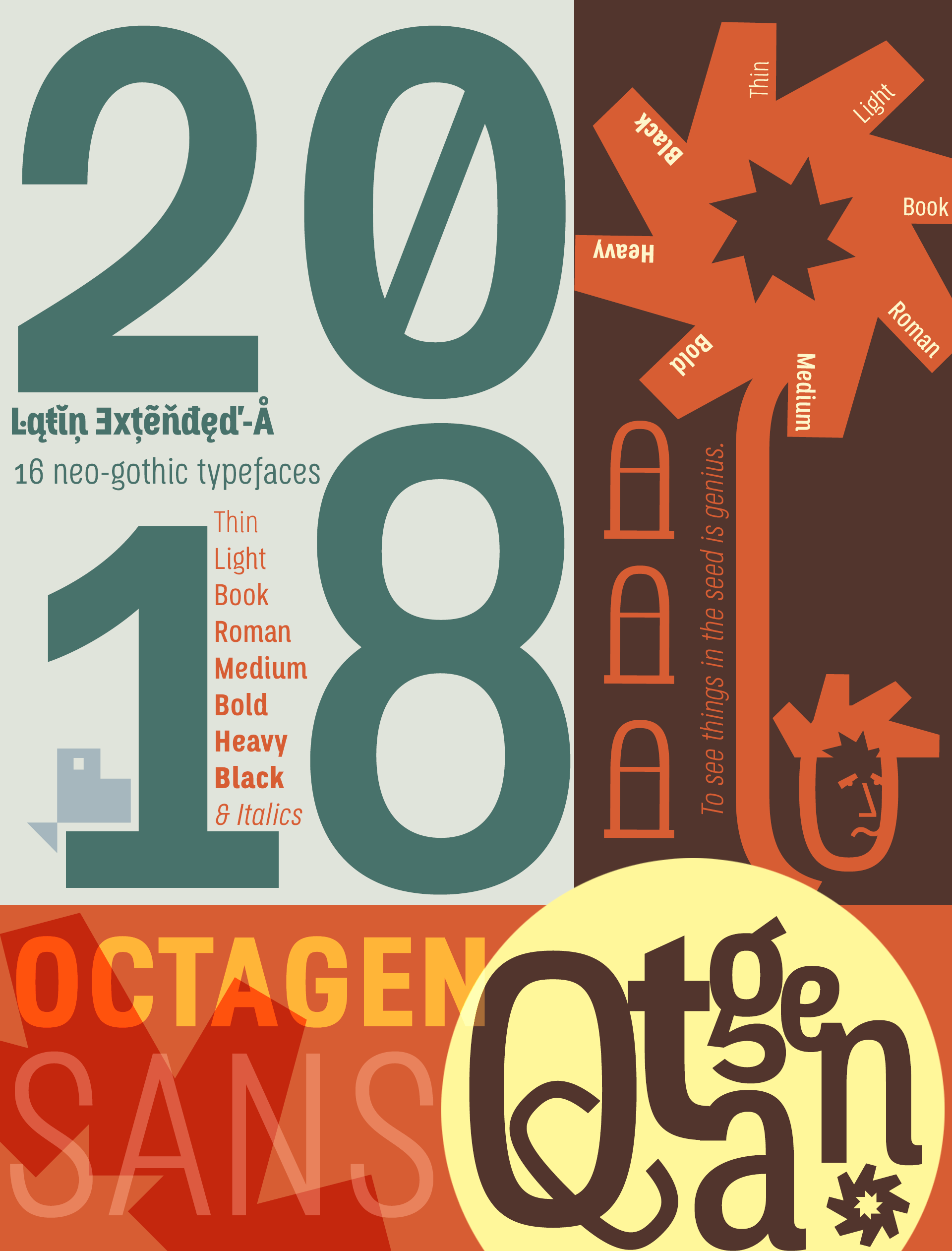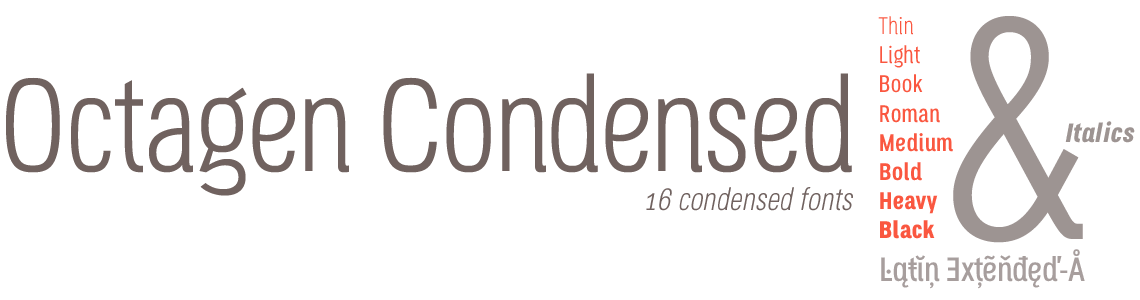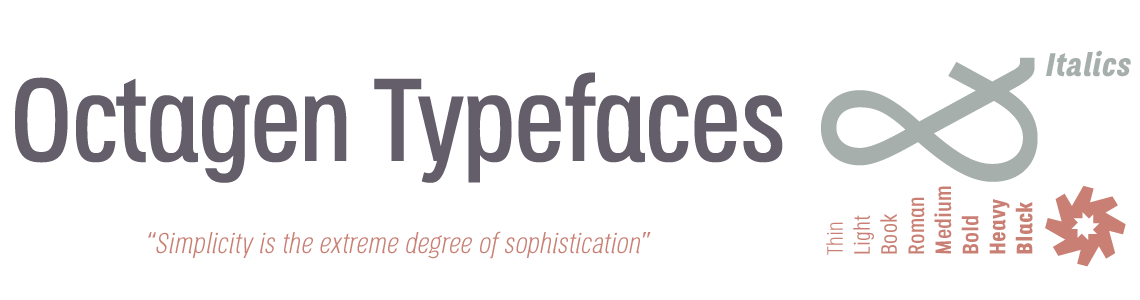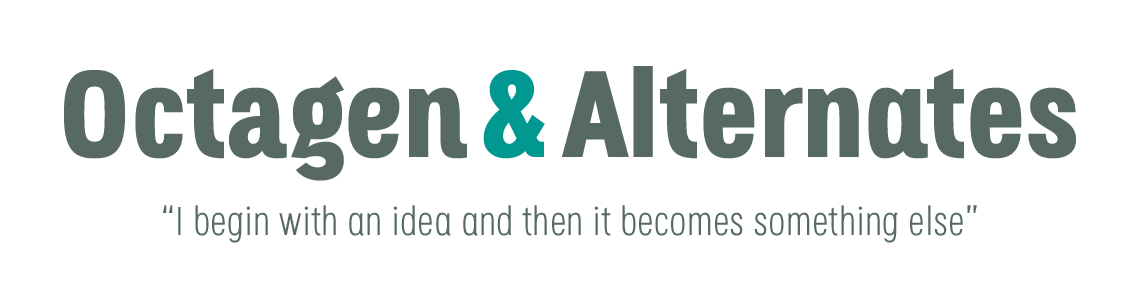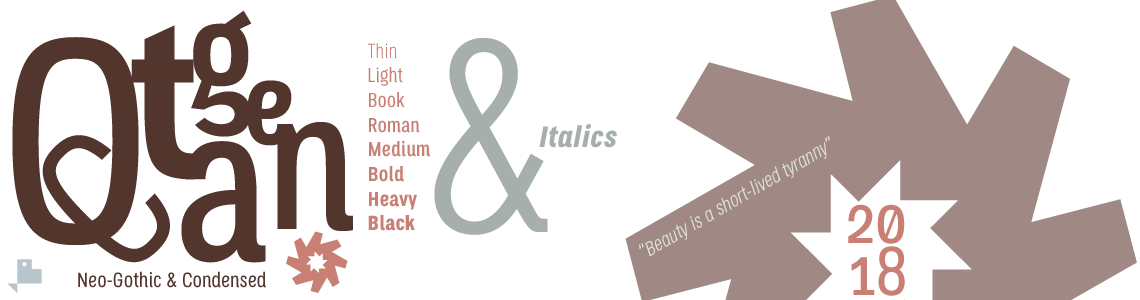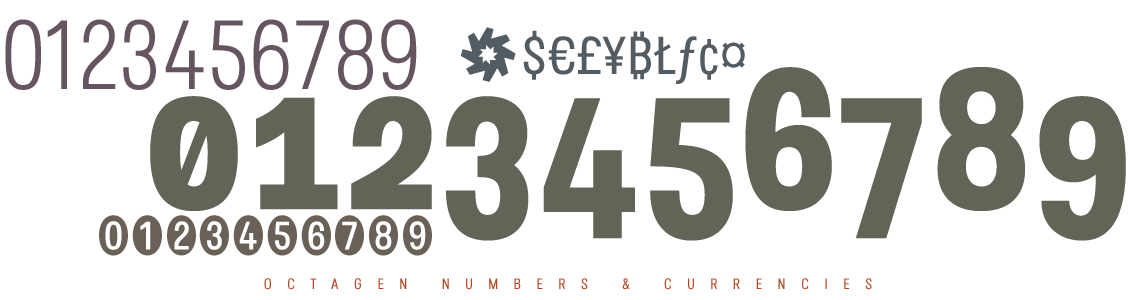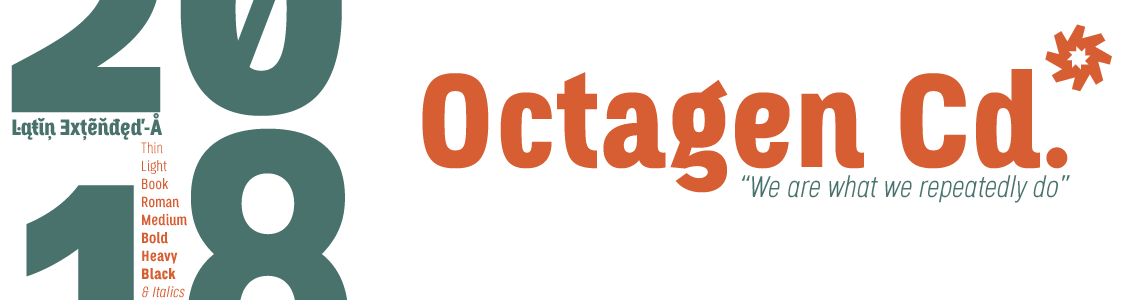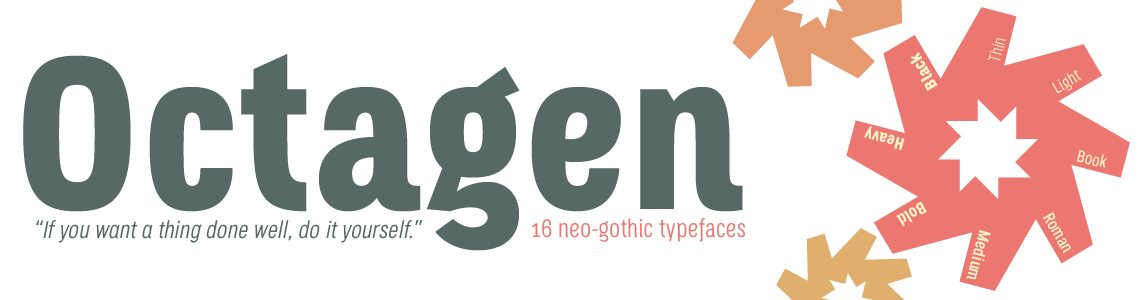
16 Fonts Neo-Gothic & Condensed
Estilo: Sans Serif, Neo-Gothic, Condensed, Italic
Proporción: Thin, Light, Book, Roman, Bold, Heavy & Black
Glyphs: 529
Funciones OpenType: Additional languages, All Alternates, Alternate Annotation Forms, Capital Spacing, Denominators, Discretionary Ligatures, Extended Fractions, Historical Forms, Historical Ligatures, Inferiors, Kerning, Localized Forms, Numerators, Oldstyle Figures, Ordinals, Scientific Inferiors, Slashed Zero, Standard Ligatures, Subscript, Superior letters, Superiors, Superscript.
Latin Extended-A & Open Type Features
Para los estilos en cursiva de Octagen he usado un juego de minúsculas sin remates terminales, más neutral que las versiones regulares, quedando esto compensado por la expresividad que aporta la inclinación de las itálicas, consiguiendo así importantes diferencias morfológicas coherentes dentro del desarrollo conceptual de esta familia tipográfica.
La tipografía dispone de 529 glifos (Latin Extended-A) con funciones avanzadas OpenType, varios juegos de números, un set completo de minúsculas alternativas de estilo neutral y el símbolo del Bitcoin, con soporte para cualquier idioma europeo o centro europeo. Octagen Condensed también incluye funciones OpenType (Compatibles con InDesign, QuarkXpress, Photoshop e Illustrator.